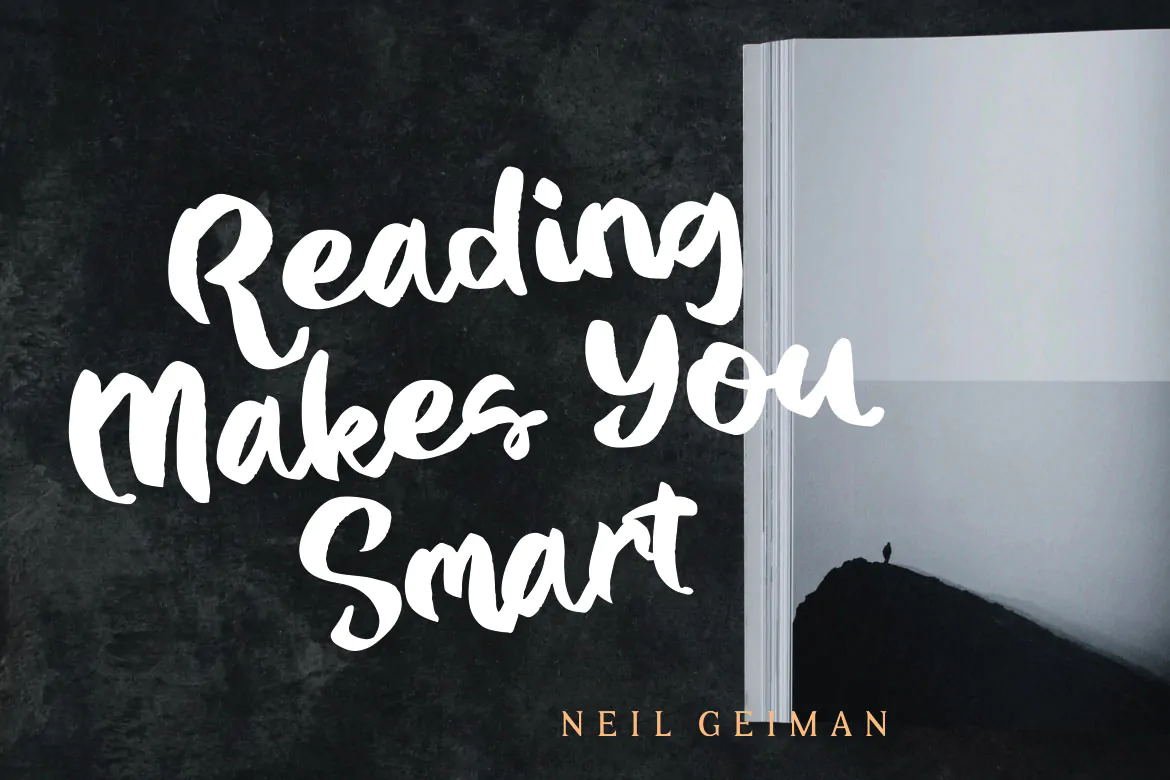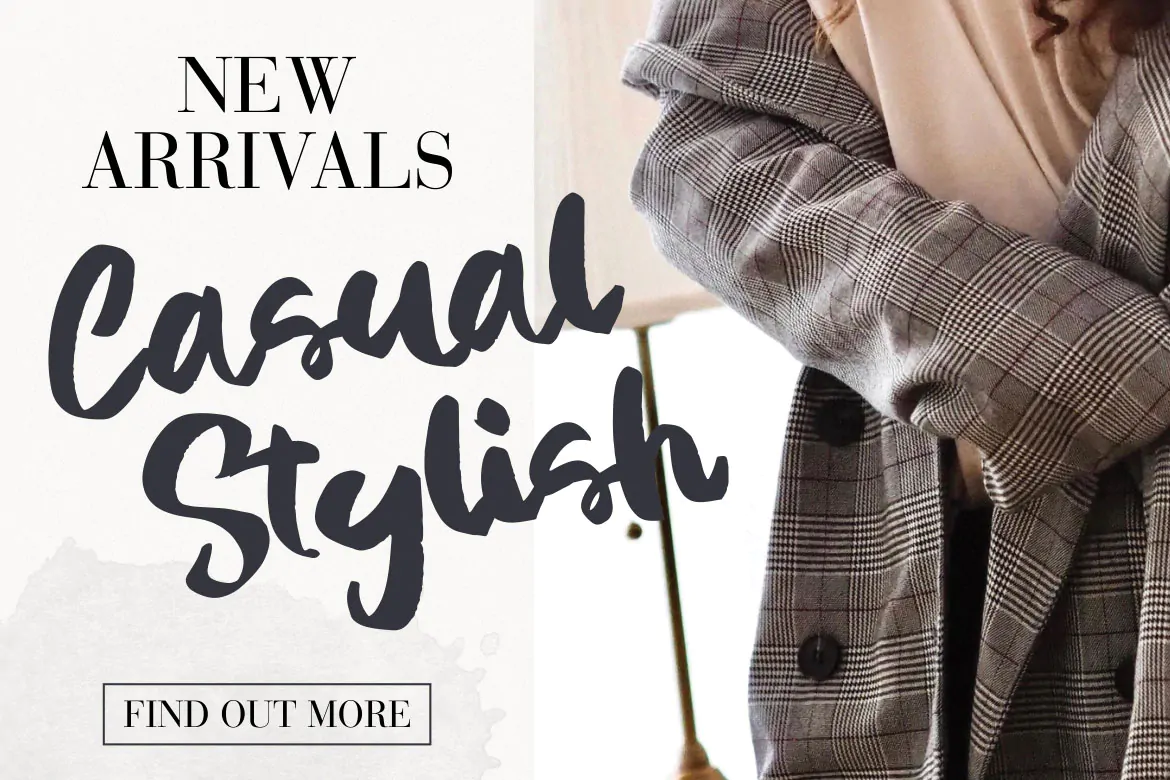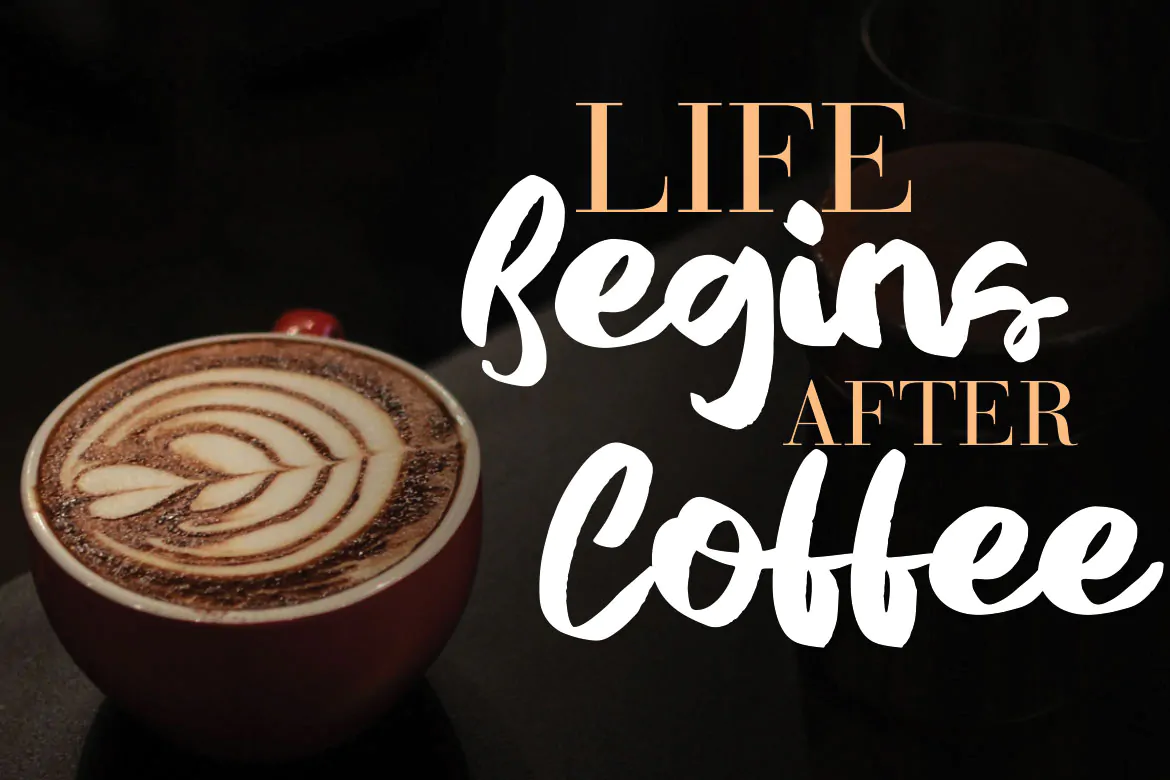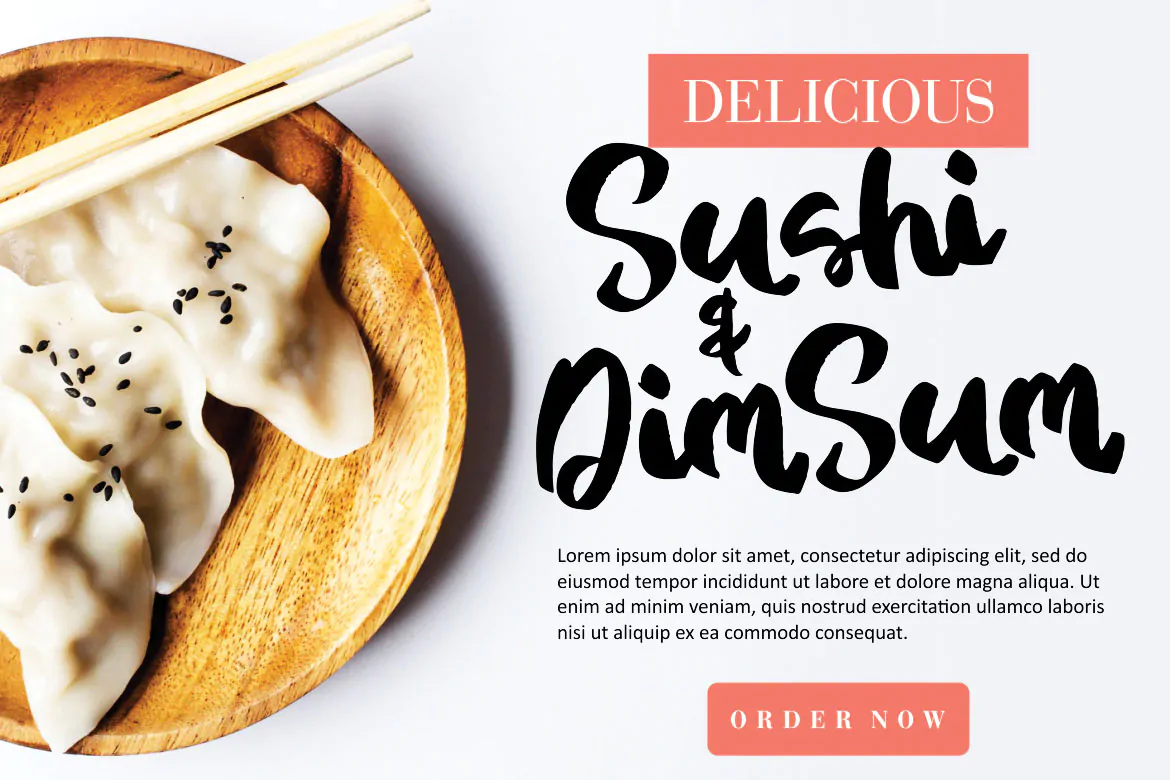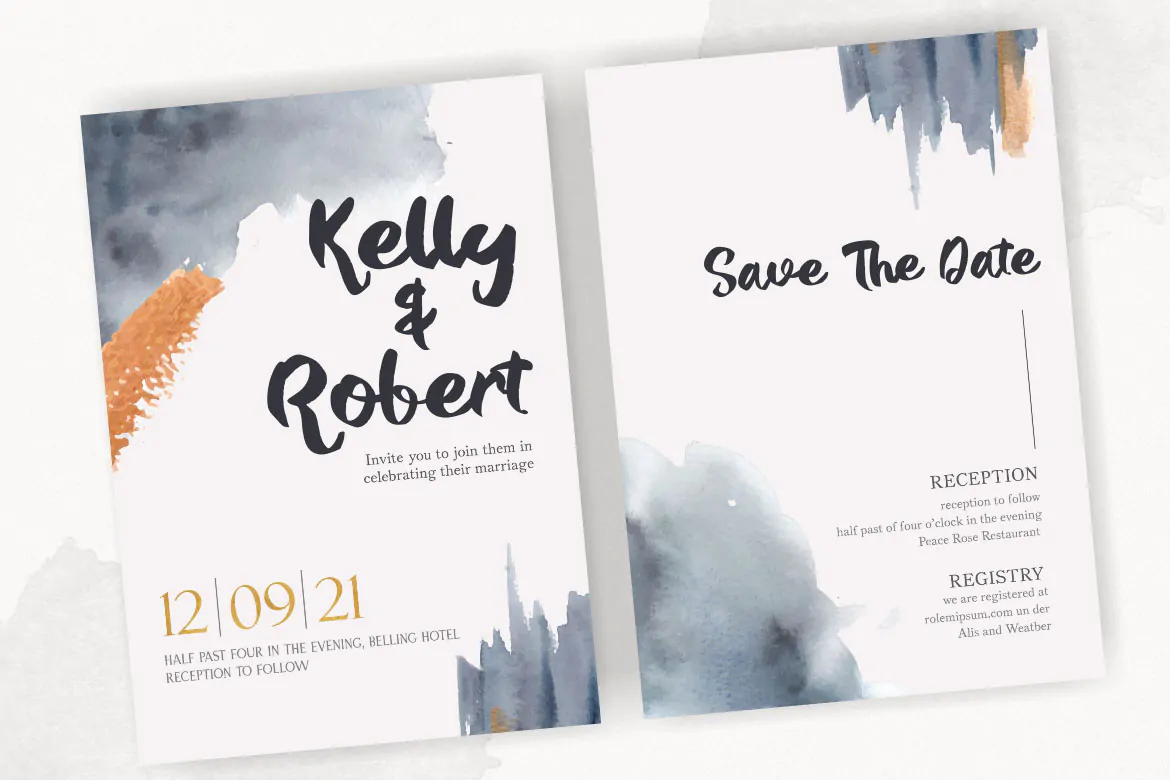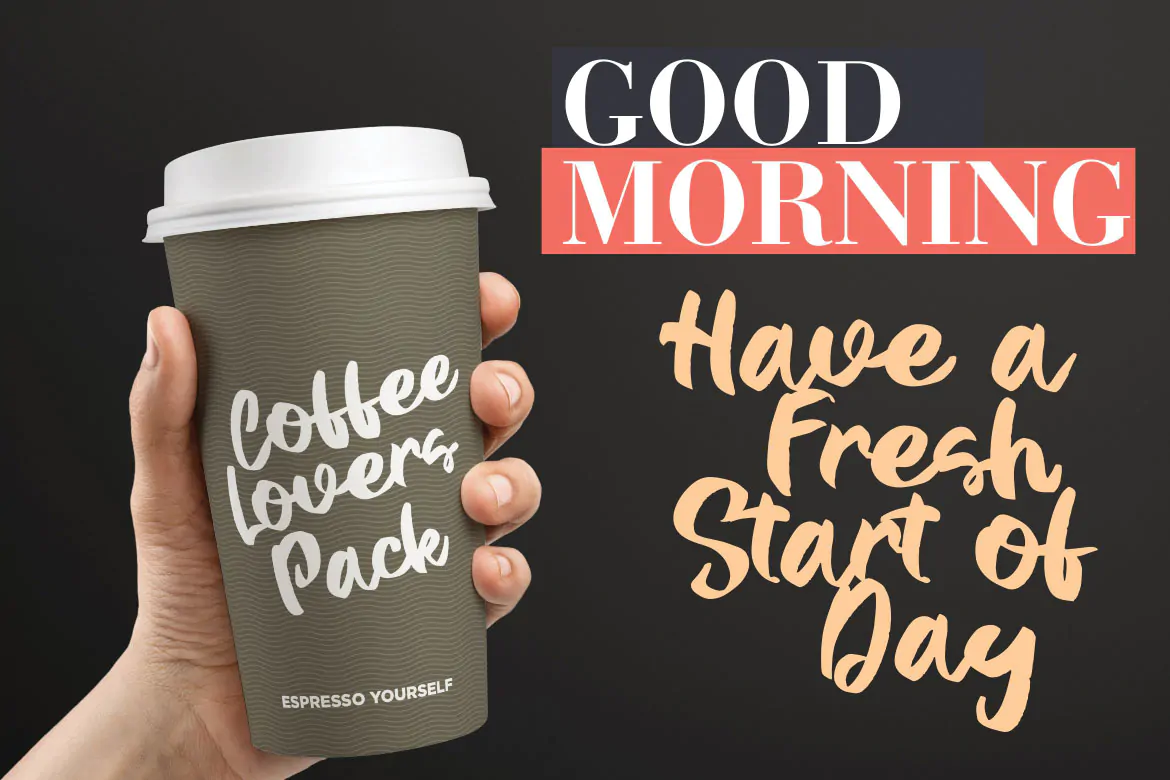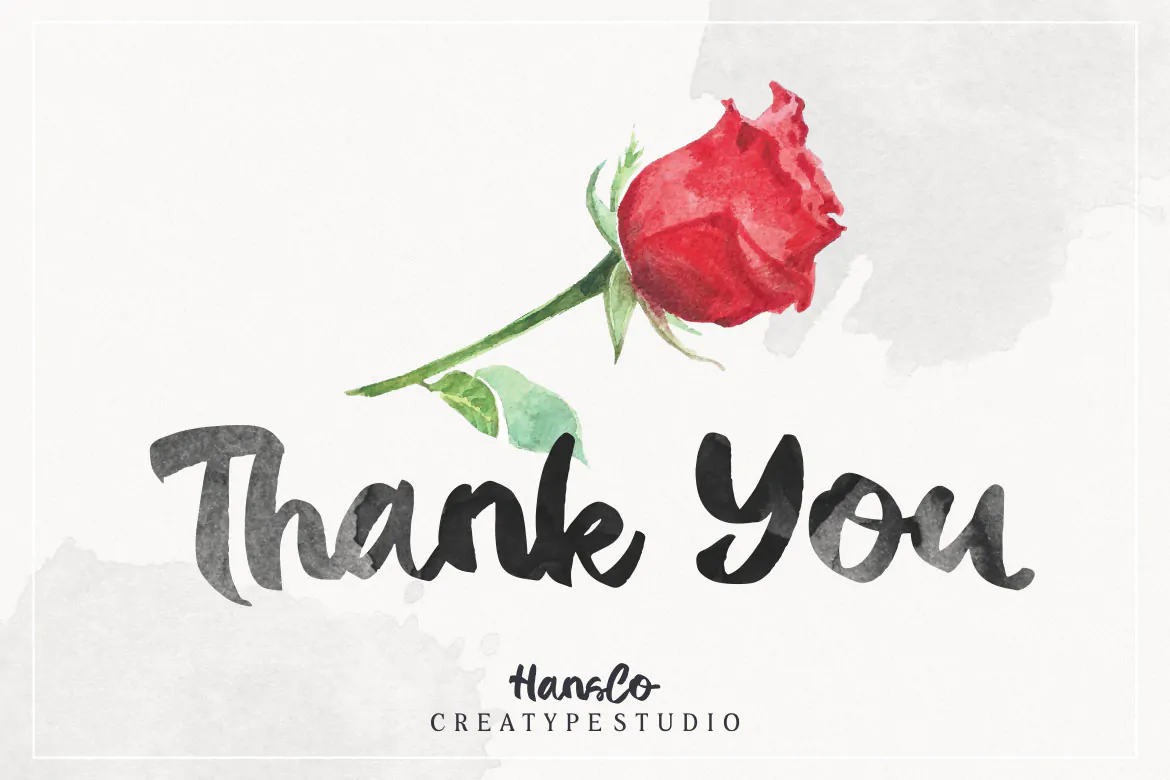
فونت جذاب بولد و کلفت Castel
فونت جذاب بولد و کلفت
فونت جذاب بولد و کلفت Castel یک اسکریپت فونت زیبای انگلیسی است که مناسب برای استفاده در طرح و پروژههای گرافیکی مختلف همچون طراحی پوستر، کاور آلبوم موسیقی، چاپ تیشرت، بسته بندی محصولات، ظروف یکبار مصرف کاغذی، لوازم التحریر و … میباشد.